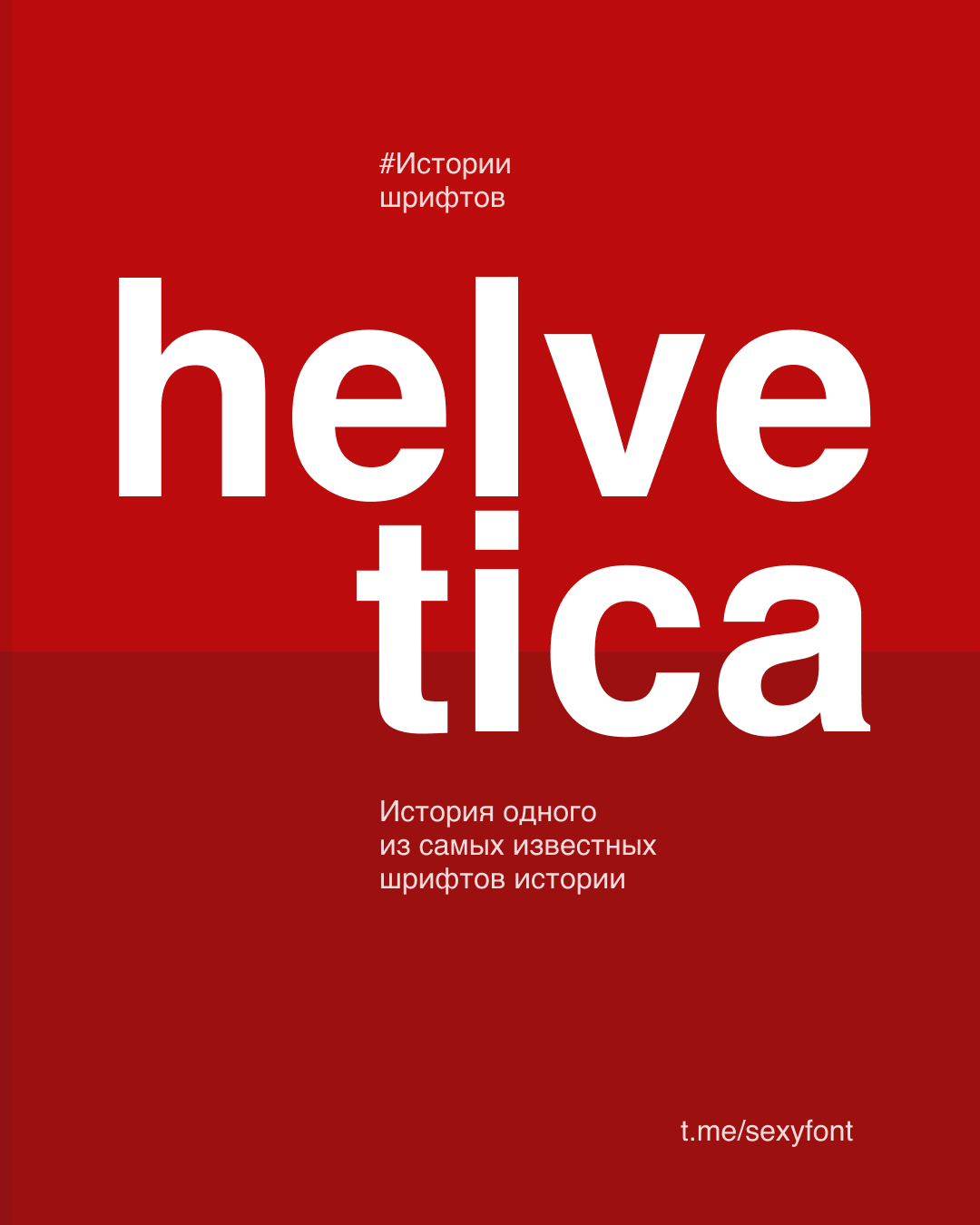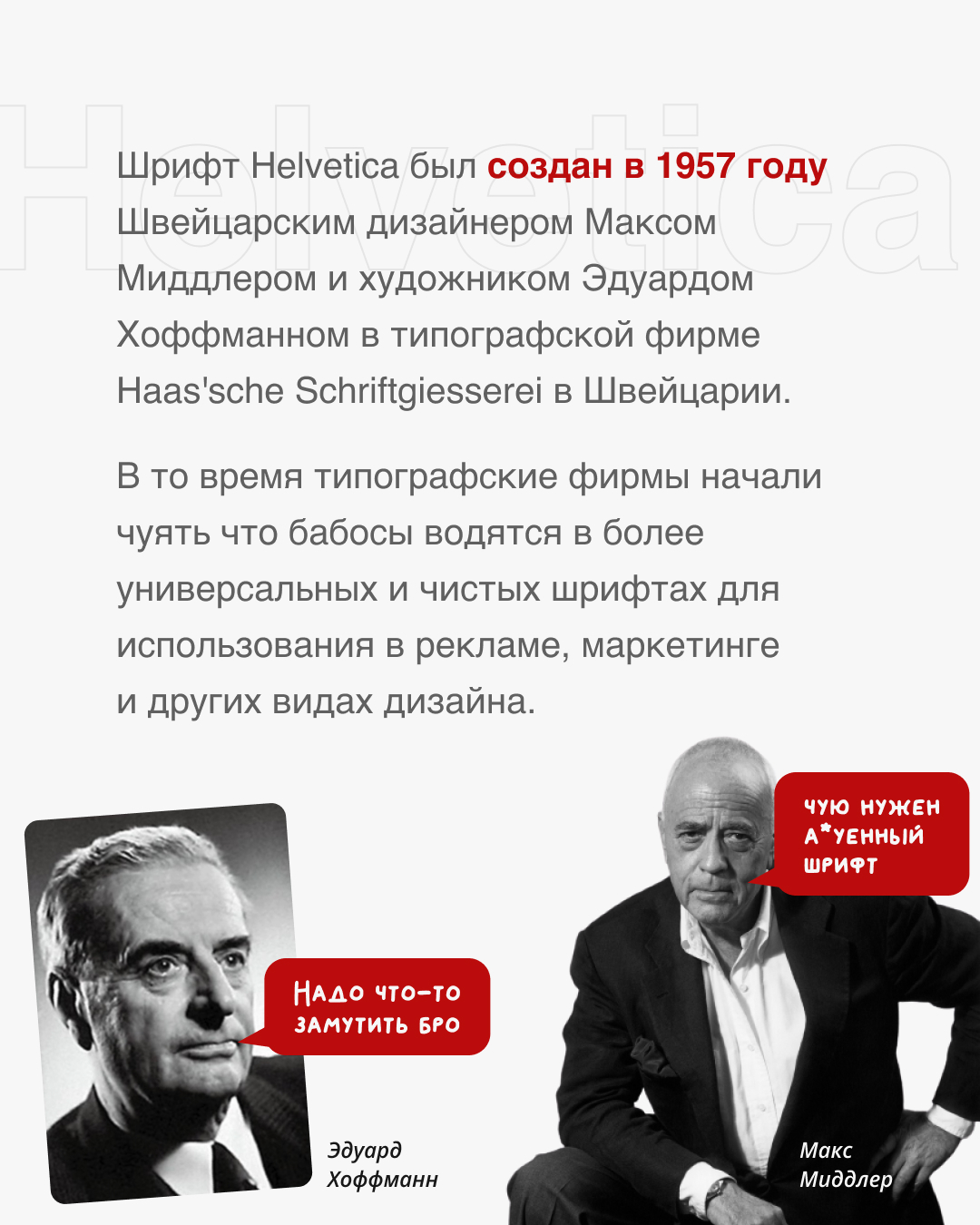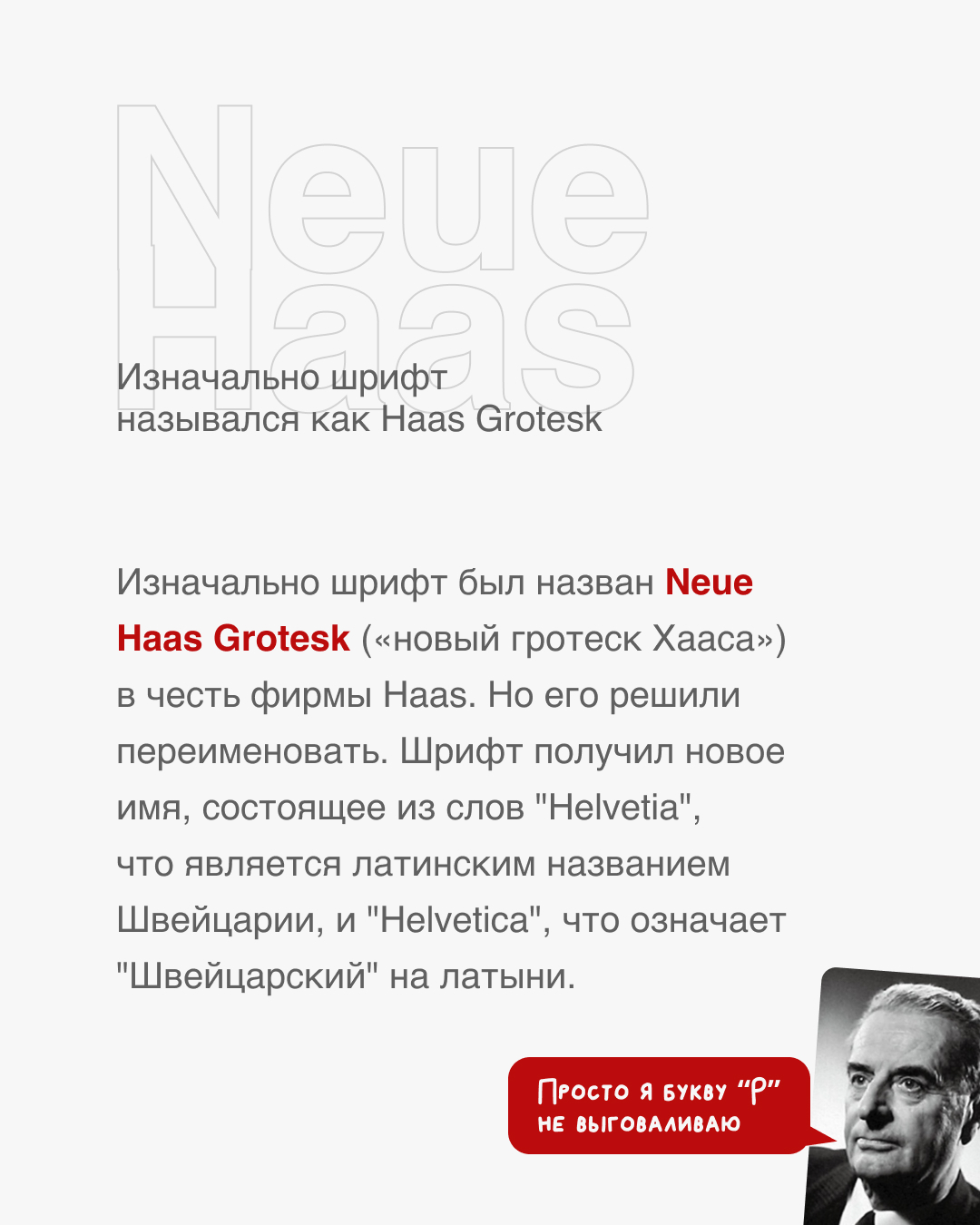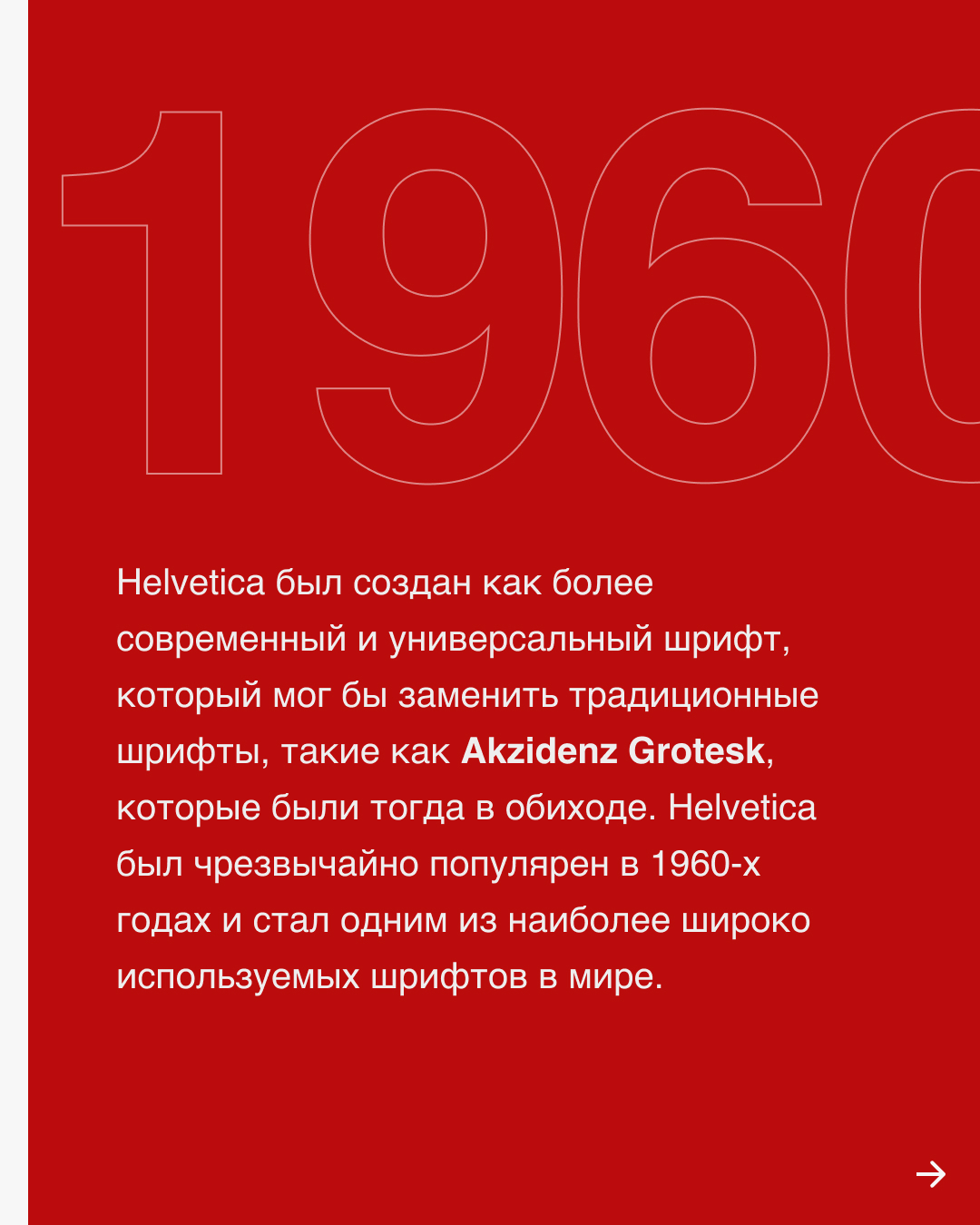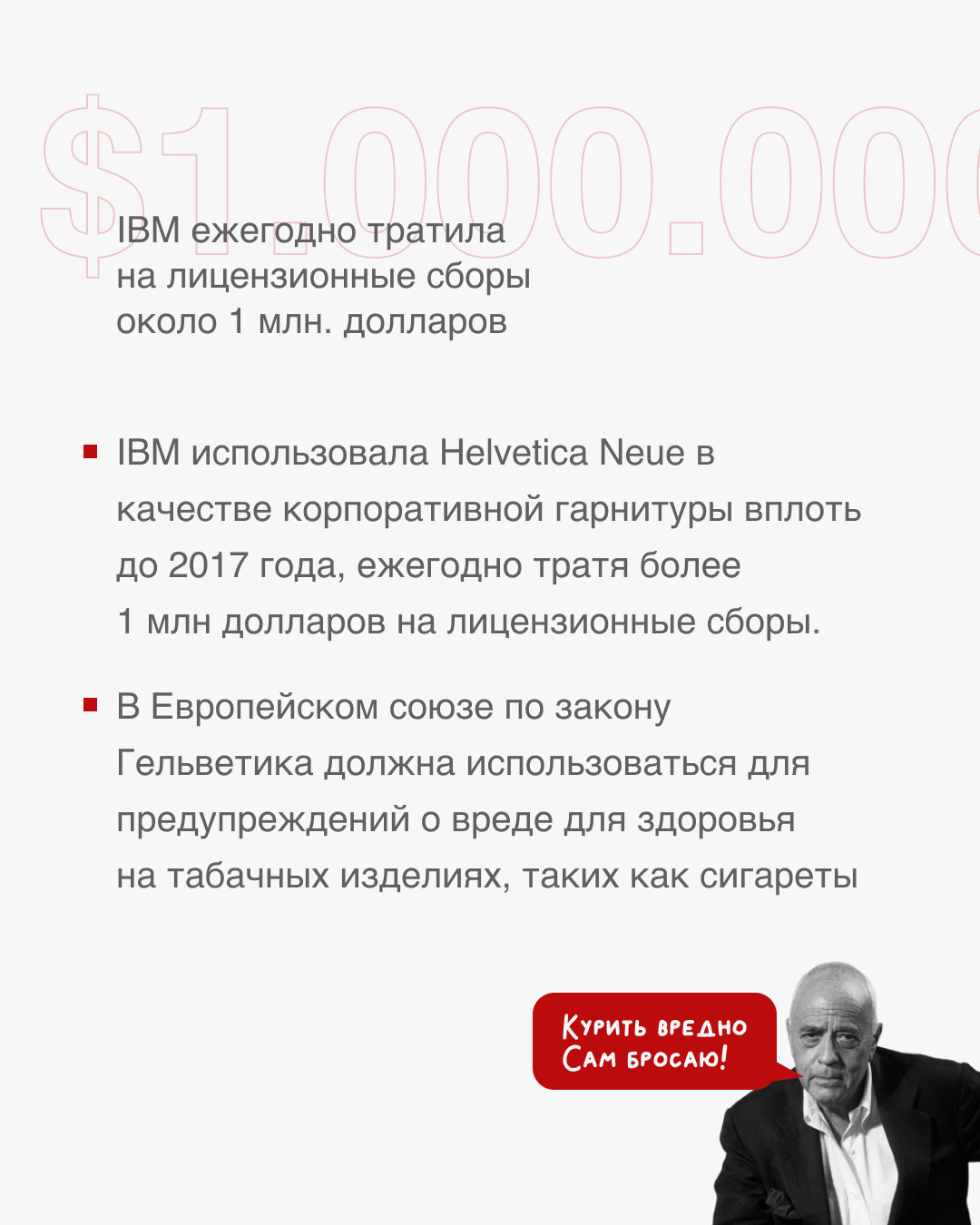
Про шрифт helvetica⁠⁠
Рубрика «истории шрифтов» Салам-пополам. Сегодня расскажу про один из самых известных шрифтов индустрии. Про шрифт, который сложно обвинить в плохой читаемости. Шрифт, которому посвящены фильмы. Неподражаемый… Helveticaaaaaaaa!!!